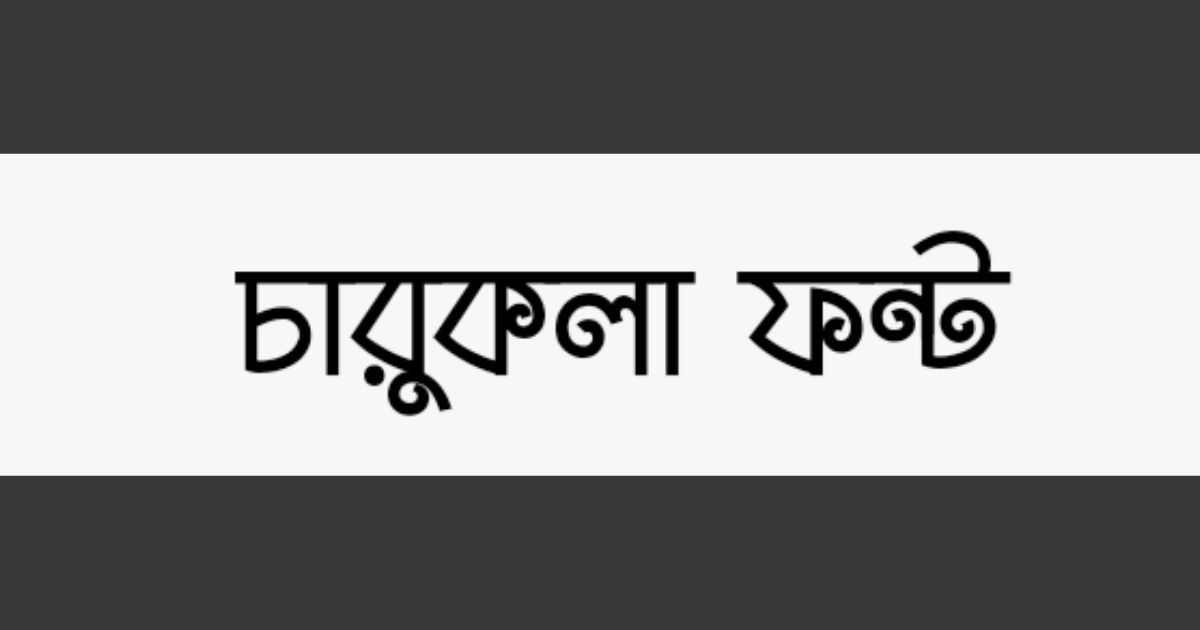
Charukola font – চারুকলা ফন্ট সকলের নিকট চেনা পরিচিত একটি বাংলা ফন্ট। Charukola font সাধারণত বিভিন্ন বাংলা লেখা লেখির কাজে সবচেয়ে বেশী ব্যবহার করা হয়।
চারুকলা ফন্ট ফ্রি একটি ফন্ট। ২০১৬ সালে এই ফন্টটি তৈরি করা হয়। Chandan Acharja, Dept. of Graphic Design, Faculty of Fine Arts, University of Dhaka চারুকলা বাংলা ফন্টটি ডেভলপ করেন। Charukola Font টির ৬ টি স্টাইল/ ধরণ এই পোস্ট থেকে বিনামূল্যে ডাউনলোড করে নিতে পারবেন। সব স্টাইলগুলো জিপ ফাইলের মধ্যে রাখা হয়েছে।
Charukola font Style
- Charukola Regular
- Charukola Bold
- Charukola Italic
- Charukola Bold Italic
- Charukola Ultra Light
- Charukola Ultra Light Italic
Short Details of Charukola Font (চারুকলা ফন্ট)
| Font Name | Charukola (চারুকলা) |
| Designer | Chandan Acharja |